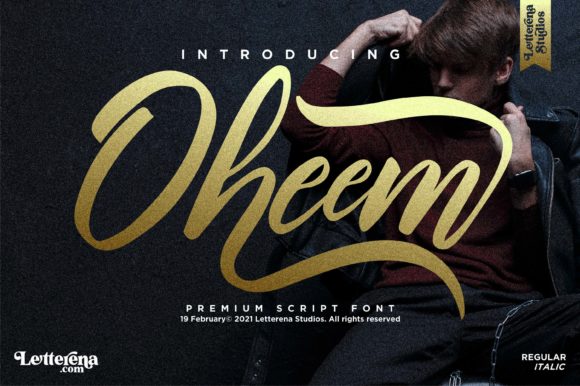
Creativefabrica Oheem Font
[Creativefabrica] Oheem Font
Oheem - красивый и уверенный рукописный шрифт, созданный, чтобы придать стильный штрих вашим заголовкам и логотипам проектов. Этот шрифт читается как сильный, уверенный и динамичный и может добавить тонны ностальгического характера вашим дизайнам.